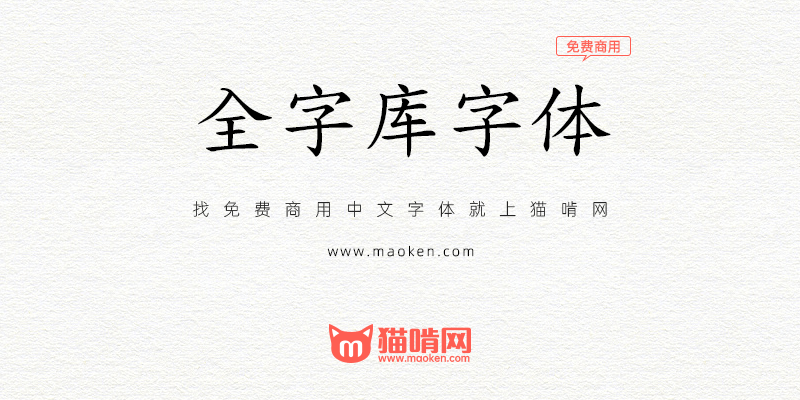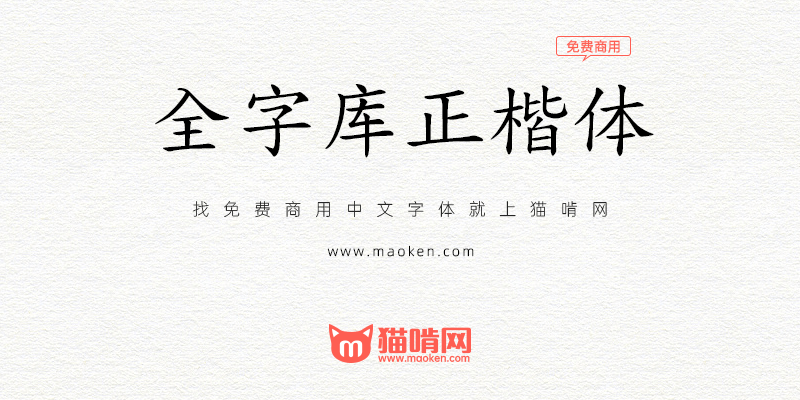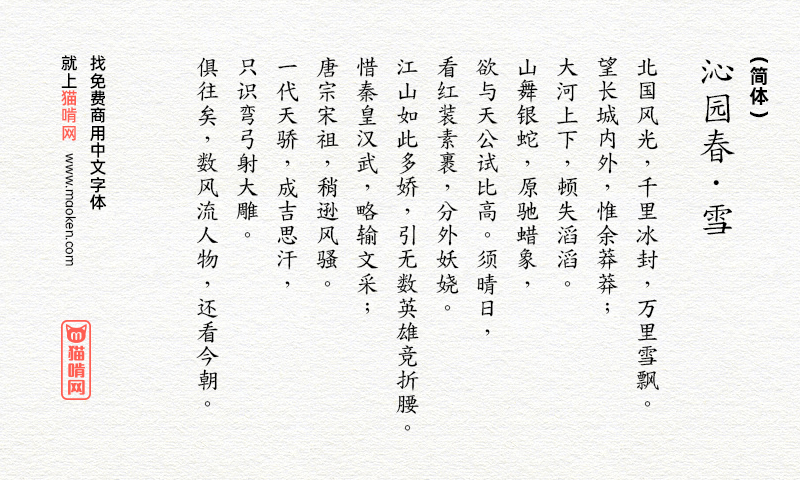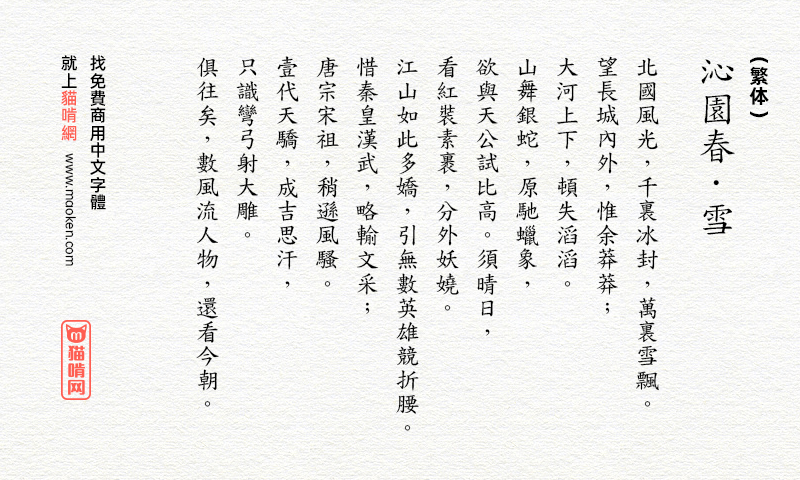
全字库正楷体:中国台湾为了标准字元编码方案而生的字体
字体作者:全字库 (中国台湾) 字体字重:1个
如果您没有足够的预算购买字体版权,总有会其它替代方案,例如使用Google和Adobe合作共同开发的思源黑体、思源宋体等都是安全可靠的选择,假如你觉得这太容易“撞字”跟其他人一样的话,中国台湾的全字库也有提供两款免费、可商用的中文字体可供下载。这两款字体分别是全字库正楷体和全字库正宋体。
CNS11643中文标准交换码全字库(简称全字库)计划从1980年开始实施,早期中国台湾为了统一资料交换使用的内码而制定的标准字元编码方案,标准交换码让不同内码也可以沟通交换内容;在全字库中则提供明体、正宋体和正楷体三种字型,使用者可以从资料开放平台免费下载。
这两款字体是为了早期中国台湾统一资料交换使用的内码而制定的标准字元编码方案,所以设计上没有什么特色,中规中矩。字符集相对来说也算比较全,喜欢的朋友可以下载使用。
这个好诶,字数很全!不知道有没有粗体版本呢?想用在老游戏上,太细了感觉会看不清楚,好像没有人做粗体字重的楷体……
同 “台湾教育部标准楷书” ,字形基本一致
• 开源免费字体很少有大字库的楷体啊,这字体大部分是台湾字形